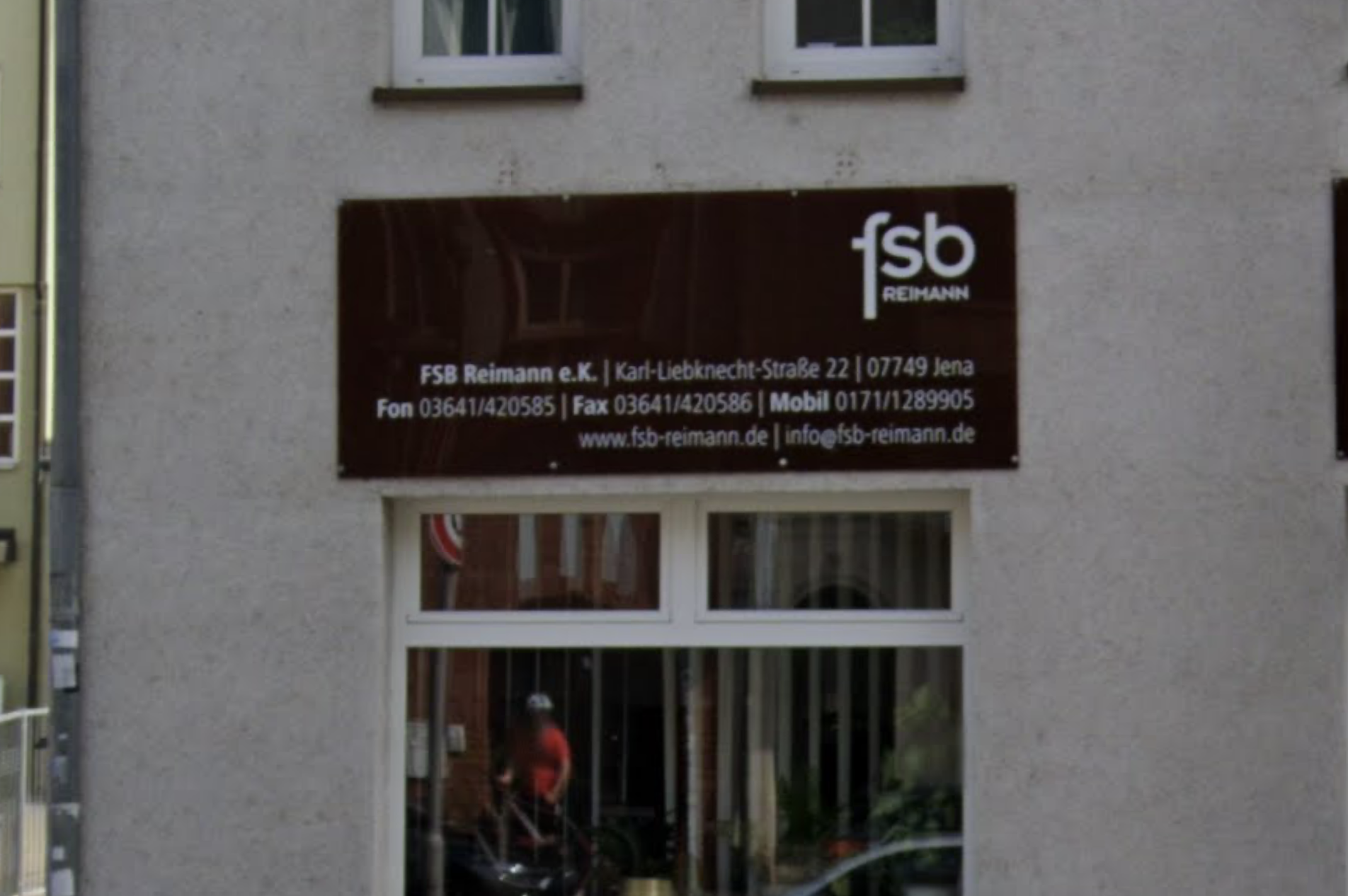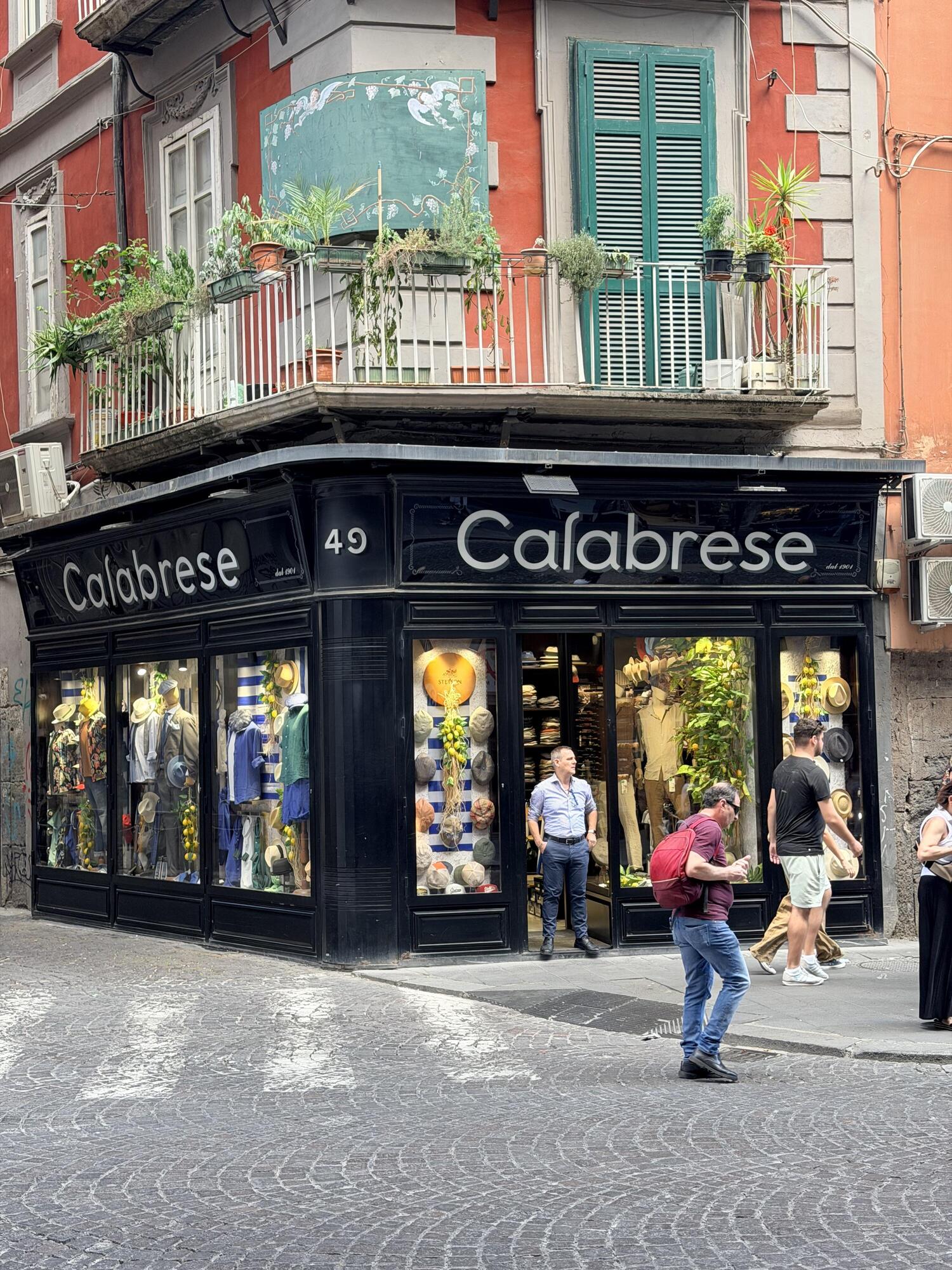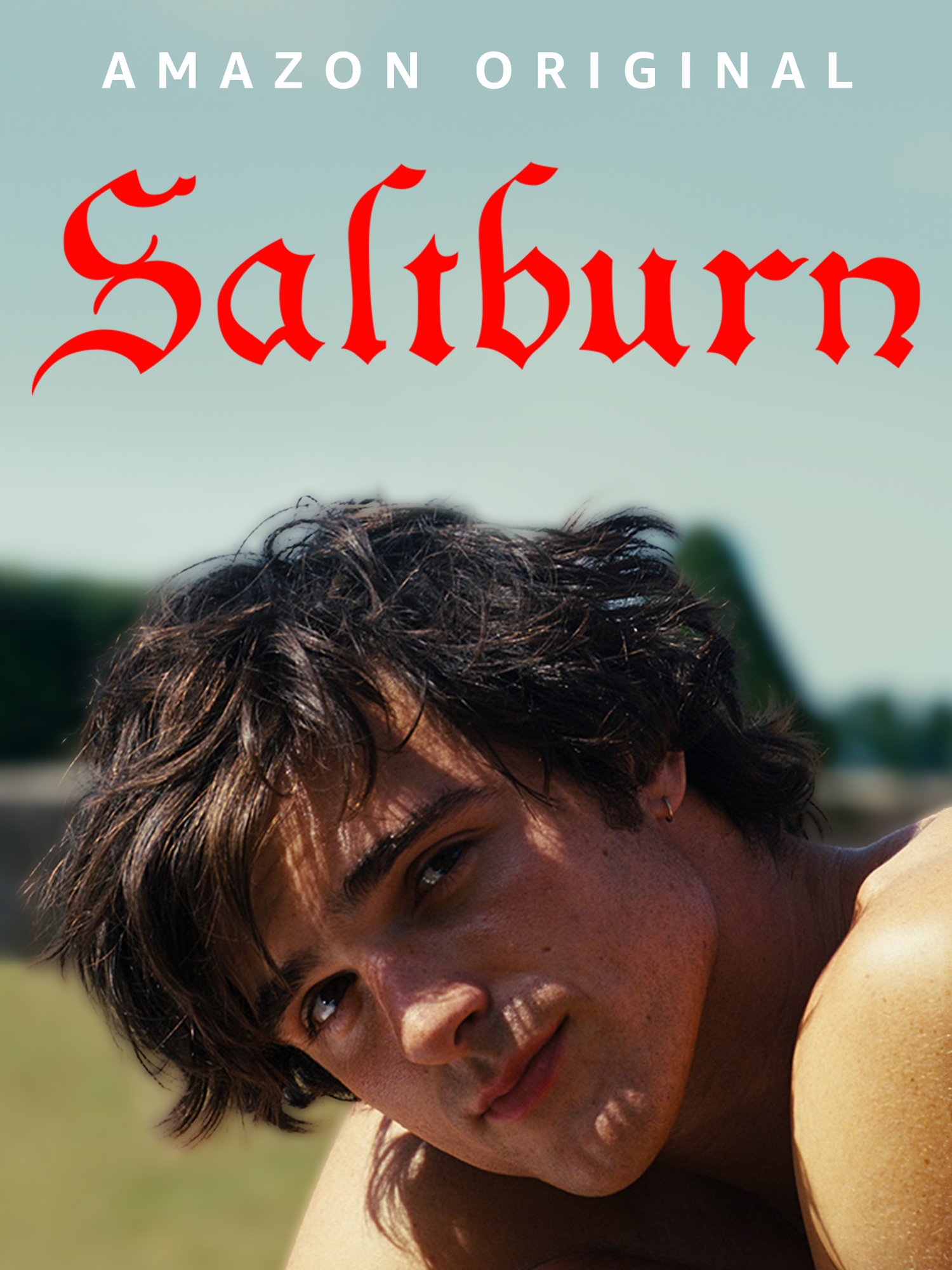
zumindest die letzten beiden beispiele scheinen mir gelungene bewusste gestaltungsentscheidungen zu sein. bei »Calabrese« hätte sich die biegung unten vermutlich eher besser eingefügt.